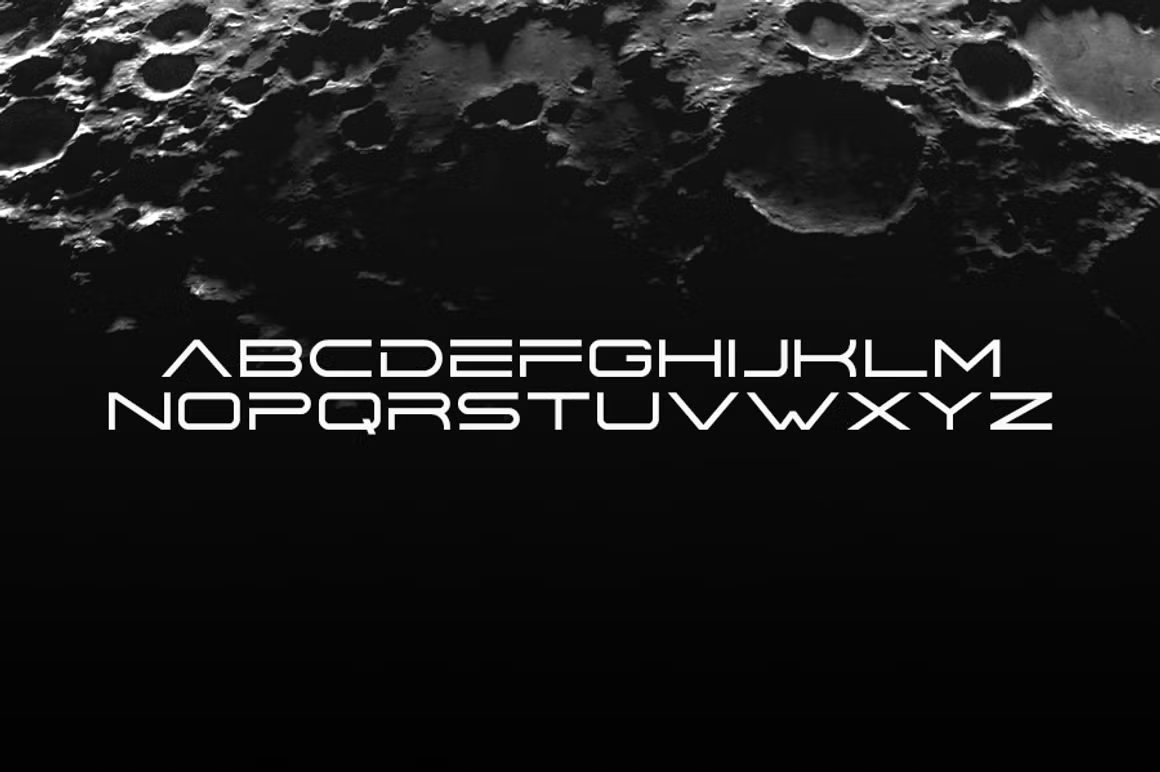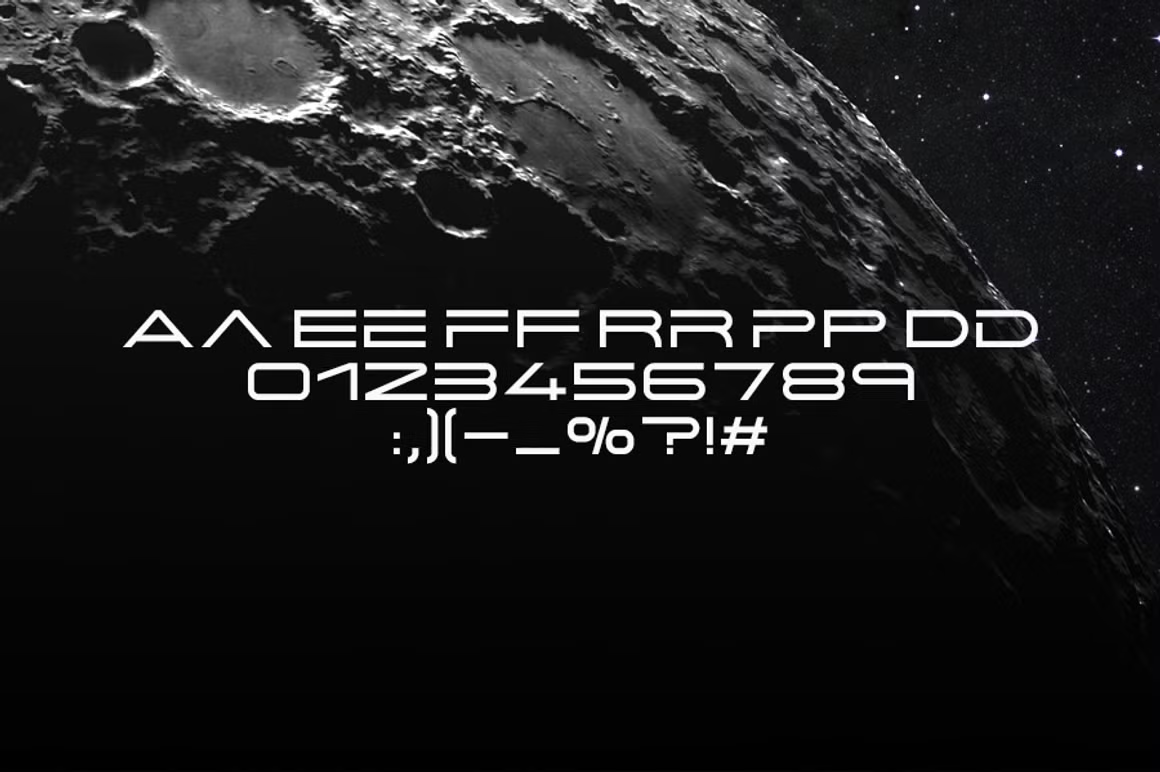
Centauri Font
Description de Centauri Font
Centauri est une police futuriste avec des lettres larges et minimalistes. Il comprend des lettres majuscules anglaises, des lettres alternatives, des signes de ponctuation de base et des chiffres.